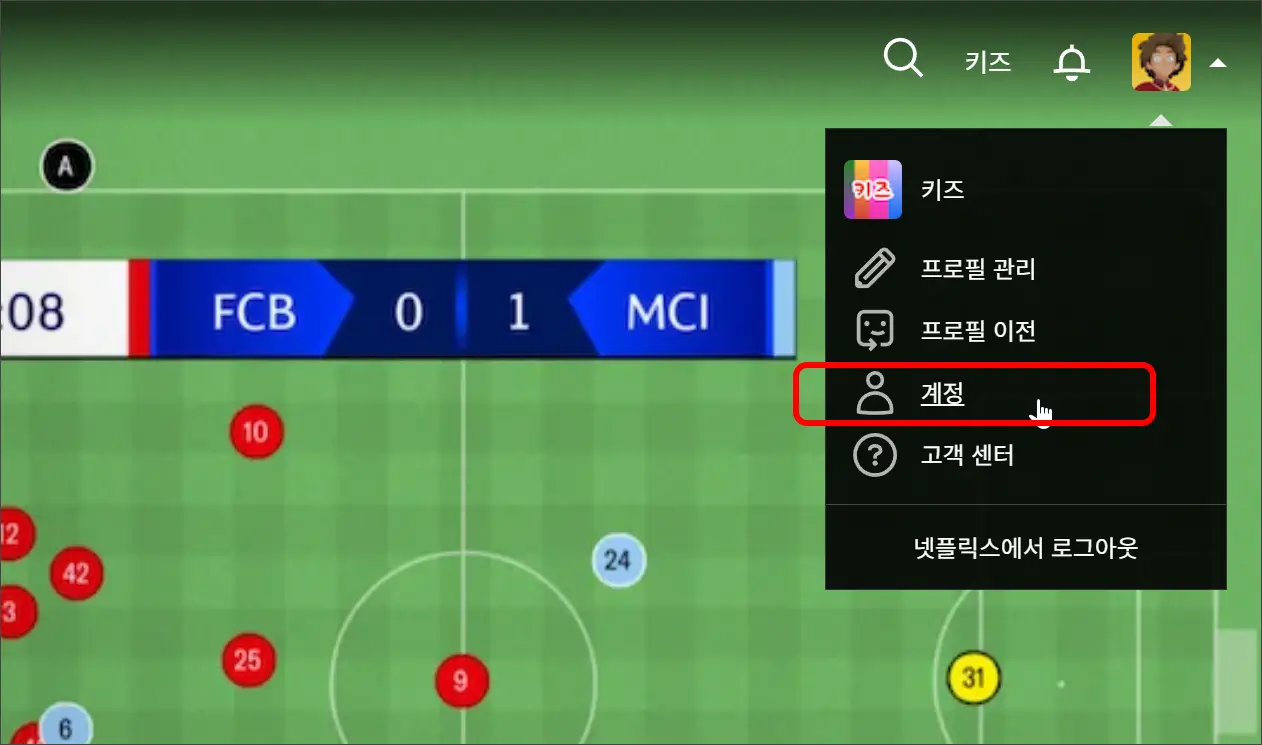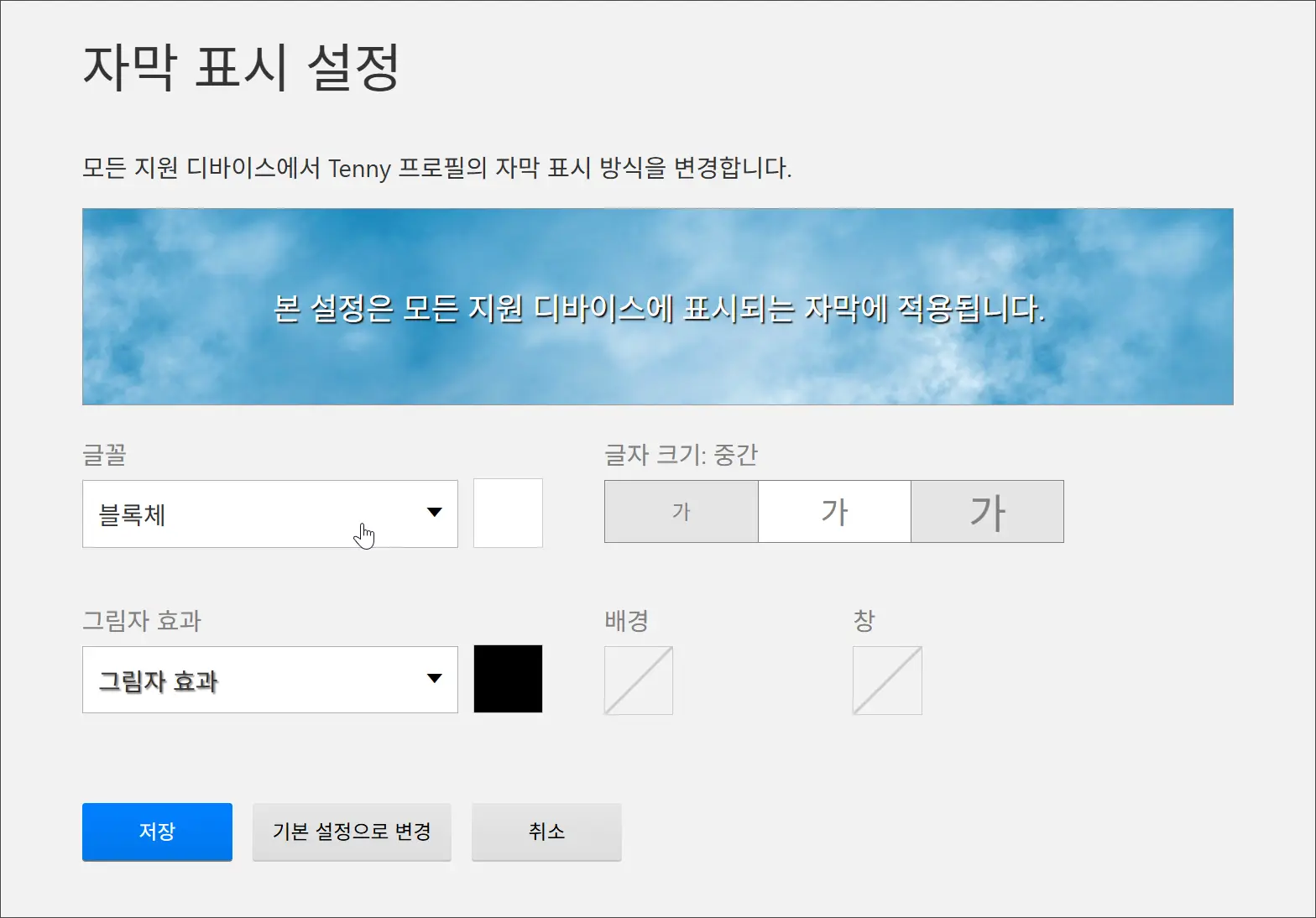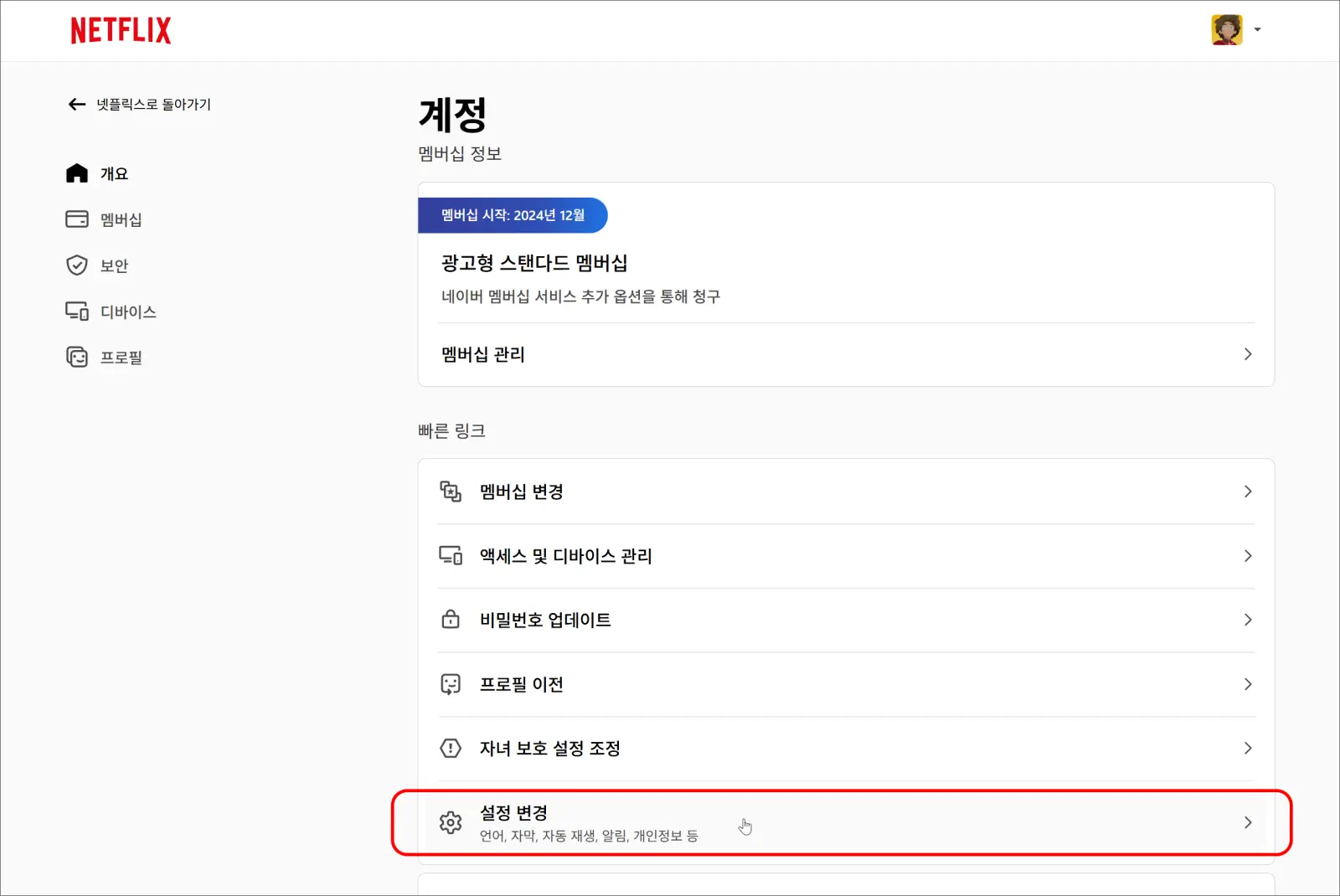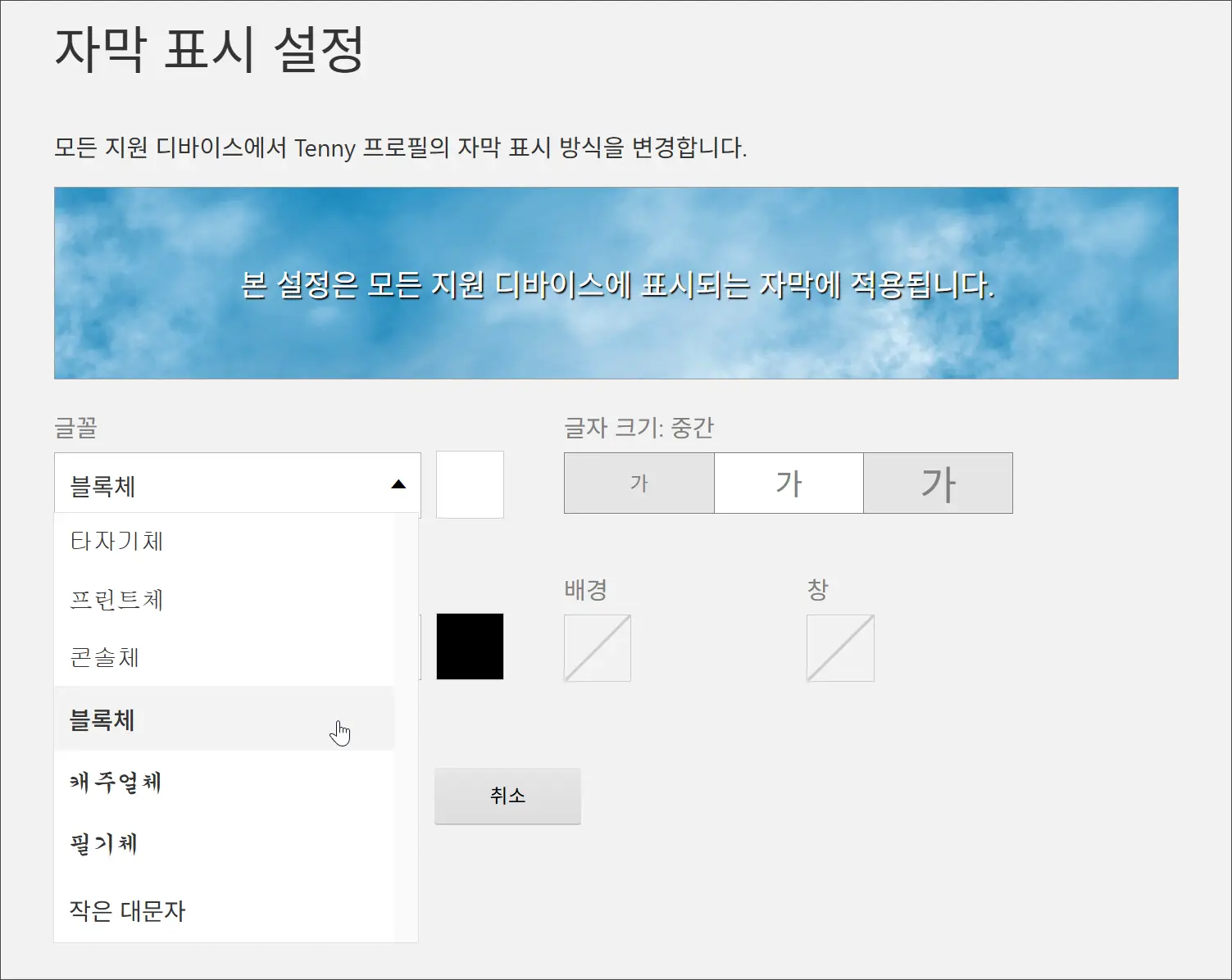
넷플릭스 PC 자막 크기/폰트(글꼴) 설정하기
넷플릭스 PC 자막, 폰트 설정 어렵지 않아요!
PC에서 넷플릭스 자막 폰트를 내 입맛에 맞게 바꾸는 방법을 찾고 계신가요? 이 글 하나면 완벽하게 해결됩니다.
솔직히 말해서, 넷플릭스에서 영화나 드라마를 볼 때 가장 몰입을 방해하는 것 중 하나가 바로 '자막'이었어요. 기본 자막 폰트가 제 취향이 아니거나, 뭔가 좀 더 눈에 잘 들어오는 폰트였으면 좋겠다는 생각을 자주 했거든요. 특히 긴 드라마를 볼 때는 자막이 너무 작거나 배경색과 비슷해서 불편했던 경험, 저만 그런 거 아니죠? 😅
다행히 넷플릭스 PC 버전에서는 이 자막 설정을 아주 쉽게 바꿀 수 있답니다! 오늘은 제가 직접 경험하면서 알아낸 넷플릭스 PC 자막 폰트 설정 방법을 자세히 알려드릴게요.
넷플릭스 자막 설정, 왜 필요할까요? 🤔
넷플릭스 PC 자막 폰트 설정은 단순히 예쁘게 보이기 위한 것만은 아니에요. 저처럼 눈이 좀 안 좋다거나, 특정 폰트가 더 편한 분들에게는 정말 필수적인 기능이 될 수 있죠. 기본 폰트가 익숙하지 않거나 읽기 불편할 때, 자막 설정을 바꾸면 훨씬 편안하게 콘텐츠를 즐길 수 있답니다.
그리고 요즘에는 자막 디자인까지 신경 쓰는 분들도 많잖아요? 넷플릭스에서는 폰트 종류부터 크기, 색상, 심지어 그림자 효과까지 다양하게 조절할 수 있어서 나만의 시청 환경을 만들 수 있다는 점이 정말 매력적이에요. 저도 처음엔 몰랐는데, 한 번 설정해두니 영화 볼 때 훨씬 몰입이 잘 되더라고요.
넷플릭스 자막 설정은 PC 웹사이트를 통해서만 변경할 수 있어요. 모바일 앱이나 스마트 TV 앱에서는 제한적인 옵션만 제공되니, 꼭 PC에서 로그인해서 설정해주세요!
PC에서 넷플릭스 자막 폰트 설정하는 방법 📊
자, 이제 본격적으로 넷플릭스 PC 자막 폰트를 설정하는 방법을 알아볼까요? 생각보다 정말 간단해서 놀라실 거예요. 제가 단계별로 차근차근 설명해 드릴게요.
먼저, 웹 브라우저를 열고 넷플릭스에 접속해서 로그인해주세요. 이 모든 설정은 넷플릭스 웹사이트에서만 가능하다는 점, 다시 한번 강조합니다!
단계별 자막 설정 가이드
넷플릭스 홈페이지에 로그인 후 우측 상단의 프로필을 선택하고, '계정'설정으로 이동합니다.
계정 설정에서 하단의 '설정 변경'을 선택합니다.
설정에서 '자막 표시 설정'을 선택합니다.
위와 같이 글꼴이나 화면 표시 효과등을 선택할 수 있습니다.
하지만, PC의 글꼴을 선택하거나 할 수 없고, 지원되는 글꼴도 그리 많지는 않습니다.
설정을 변경한 후에는 반드시 하단의 '저장' 버튼을 눌러주셔야 변경 사항이 적용됩니다. 저장하지 않고 페이지를 닫으면 설정이 초기화될 수 있어요!
자막 설정, 어떤 옵션들이 있을까요? 🧮
넷플릭스 자막 설정 페이지에 들어가 보면 정말 다양한 옵션들을 만날 수 있어요. 저도 처음엔 뭐가 뭔지 몰라서 이것저것 눌러봤답니다. 대표적인 옵션들을 소개해 드릴게요.
📝 주요 자막 설정 옵션
폰트 종류, 폰트 색상, 폰트 크기, 그림자 효과, 배경, 창, 리셋
더 나은 시청 경험을 위한 자막 설정 팁 👩‍💼👨‍💻
자막 설정은 단순히 보기 좋게 만드는 것을 넘어, 콘텐츠 몰입도를 높이는 데 큰 역할을 해요. 제가 개인적으로 활용하는 몇 가지 팁을 공유해 드릴게요.
자막 폰트 크기는 화면 크기와 시청 거리에 따라 조절하는 것이 중요해요. 너무 작으면 눈이 아프고, 너무 크면 화면을 가릴 수 있거든요.
실전 예시: 나만의 '최애' 자막 스타일 만들기 📚
제가 요즘 가장 즐겨 사용하는 자막 스타일을 예시로 보여드릴게요. 저는 눈이 좀 피로한 편이라 시인성이 좋은 폰트와 대비되는 색상을 선호하는 편이에요.
사례: A씨의 최애 자막 스타일
• 폰트 종류: 모노스페이스 (Monospace) - 코드가 섞인 화면에서 특히 잘 어울리고, 또렷한 느낌을 줘요.
• 폰트 크기: 20px - 제 노트북 화면에서는 가장 눈에 편안한 크기더라고요.
계산 과정 (시인성 최적화)
1) 콘텐츠 장르 분석: 액션/SF 장르에선 빠른 대사 전달을 위해 또렷한 폰트 선호
2) 시청 환경 고려: 주로 밤에 시청하므로 눈부심 방지를 위해 어두운 배경에 밝은 자막 선호
최종 결과
- 폰트 색상: 밝은 노란색 (#FFFF00) - 어두운 화면에서도 선명하게 보여요.
- 그림자 효과: 검은색 그림자 (그림자 불투명도 75%) - 글씨가 배경에 묻히지 않고 입체적으로 보이게 해줘요.
이렇게 설정해두니 영화나 드라마를 볼 때 자막 때문에 신경 쓸 일이 없어서 너무 좋아요. 특히 외국어 콘텐츠를 볼 때 번역에 집중할 수 있어서 학습 효과도 더 커지는 것 같고요!
오늘은 넷플릭스 PC 자막 폰트를 내 취향에 맞게 설정하는 방법을 자세히 알아봤어요. 복잡하게 생각할 필요 없이, 몇 번의 클릭만으로 나만의 최적의 시청 환경을 만들 수 있답니다.
1. 넷플릭스 자막 설정은 PC 웹사이트에서만 가능해요. 모바일이나 TV 앱에서는 제한적이라는 점 기억하세요!
2. '계정' 메뉴로 이동 후 '프로필 & 자녀 보호 설정'에서 해당 프로필의 '자막 표시'를 선택합니다.
3. 폰트 종류, 크기, 색상, 그림자, 배경, 창 등 다양한 옵션을 조절할 수 있어요. 미리보기로 바로 확인하며 원하는 대로 설정해보세요.
4. 변경 후에는 반드시 '저장' 버튼을 눌러야 적용됩니다.
5. 눈의 피로도를 줄이고 몰입감을 높이려면, 화면 크기와 시청 거리를 고려해서 폰트 크기와 색상을 조절하는 게 좋아요.
넷플릭스 PC 자막 설정 핵심 요약
✨ 첫 번째 핵심: PC 웹사이트에서만 자막 설정 가능! 모바일 앱은 제한적이에요.
📊 두 번째 핵심: 계정 > 프로필 & 자녀 보호 설정에서 '자막 표시'로 진입!
🧮 세 번째 핵심:
내 취향대로 폰트 종류, 크기, 색상, 효과 등 조절!
👩‍💻 네 번째 핵심: 변경 후 반드시 '저장' 버튼 클릭 필수!
자주 묻는 질문 ❓
Q: 넷플릭스 자막 폰트 설정을 왜 PC에서만 해야 하나요?
A: 넷플릭스 모바일 앱이나 스마트 TV 앱은 시스템 제약으로 인해 PC 웹사이트만큼 다양한 자막 설정 옵션을 제공하기 어렵습니다. PC 웹사이트가 가장 유연한 설정 환경을 제공해요.
Q: 자막 설정을 저장했는데 다시 원래대로 돌아왔어요. 왜 그렇죠?
A: 자막 설정을 변경한 후 '저장' 버튼을 누르지 않았거나, 다른 프로필로 로그인하여 시청했을 가능성이 높아요. 반드시 변경하려는 프로필에서 설정하고 저장했는지 확인해주세요.
Q: 모든 콘텐츠에 제가 설정한 자막이 적용되나요?
A: 네, 특정 프로필에서 설정한 자막 스타일은 해당 프로필로 시청하는 모든 콘텐츠에 적용됩니다. 하지만, 간혹 콘텐츠 자체에 내장된 자막 스타일이 우선 적용되는 경우가 있을 수 있어요.
Q: 폰트 종류 중에 한글 폰트도 선택할 수 있나요?
A: 넷플릭스에서 기본적으로 제공하는 폰트 종류는 제한적입니다. 특정 한글 폰트를 직접 업로드하는 기능은 제공하지 않아요. 하지만 제공되는 폰트 중에서 한글 표현에 적합한 폰트를 선택할 수 있습니다.
Q: 자막 배경이나 창 색상도 바꿀 수 있나요?
A: 네, 가능합니다. 자막 설정 페이지에서 폰트 색상 외에도 배경색, 창 색상, 심지어 투명도까지 조절하여 자막의 가독성을 높일 수 있어요. 어두운 영상에서는 밝은 배경을, 밝은 영상에서는 어두운 배경을 설정하면 좋아요.